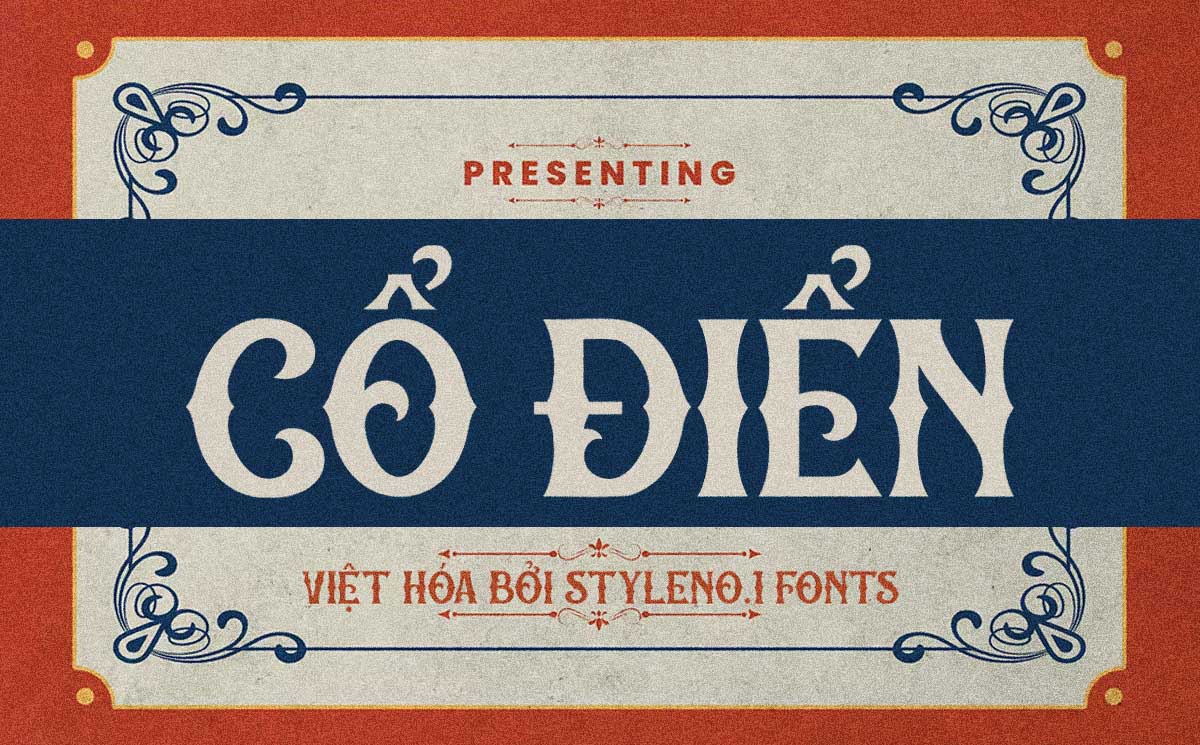
Font chữ phong cách cổ điển, vintage SVN Heimer Việt hóa là một trong những lựa chọn hàng đầu dành cho các nhà thiết kế đang tìm kiếm sự sang trọng, hoài cổ và độc đáo cho dự án đồ họa của mình. Được chế tác tỉ mỉ với bộ đường nét tinh tế cùng khả năng hiển thị tiếng Việt hoàn hảo, bộ phông chữ này mang đến làn gió mới cho các tác phẩm truyền thông và nhận diện thương hiệu. Đặc biệt, bạn có thể dễ dàng tải về và sở hữu bộ phông chữ miễn phí chất lượng cao này để thỏa sức sáng tạo không giới hạn.
Trong xu hướng thiết kế truyền thông hiện đại, phong cách vintage và cổ điển (retro) chưa bao giờ mất đi vị thế vốn có của mình. Việc kết hợp giữa hơi thở hoài cổ của những thập niên trước với ngôn ngữ thiết kế đương đại luôn tạo ra sức hút thị giác đặc biệt đối với người xem. Font chữ phong cách cổ điển, vintage SVN Heimer Việt hóa chính là một tác phẩm typography tuyệt vời đáp ứng trọn vẹn yêu cầu khắt khe đó. Với các đường nét serif sắc sảo, tỉ lệ chữ được tính toán kỹ lưỡng cùng cảm giác ấm áp, phong nhã, SVN Heimer giúp nâng tầm giá trị cho mọi tác phẩm đồ họa. Bộ phông chữ miễn phí này không chỉ đơn thuần là công cụ thể hiện văn bản, mà còn là linh hồn giúp truyền tải câu chuyện thương hiệu một cách giàu cảm xúc nhất.
1. Đường nét hoài cổ mang đậm dấu ấn nghệ thuật vượt thời gian
SVN Heimer sở hữu phong cách thiết kế mang đậm tính lịch sử, gợi nhớ đến các ấn phẩm in ấn cao cấp của thế kỷ 20. Cấu trúc chữ được xây dựng dựa trên sự cân bằng hoàn hảo giữa các nét thanh và nét đậm, tạo nên độ tương phản vừa phải, giúp văn bản vừa dễ đọc vừa giữ được nét quyến rũ riêng biệt. Những chi tiết bo tròn nhẹ nhàng ở chân chữ (serif) kết hợp với các đường cong uốn lượn tinh tế tạo nên vẻ đẹp sang trọng và đẳng cấp. Khi áp dụng vào các tiêu đề lớn, banner quảng cáo hay thiết kế logo, SVN Heimer ngay lập tức thu hút ánh nhìn của thị giác và truyền tải thông điệp về sự uy tín, tinh tế cùng bề dày lịch sử. Đây chính là yếu tố then chốt khiến các nhà thiết kế yêu thích phong cách cổ điển luôn lựa chọn SVN Heimer làm điểm nhấn trong sản phẩm của mình.
2. Bộ ký tự Việt hóa hoàn chỉnh và tối ưu hóa typography
Một trong những rào cản lớn nhất mà các designer tại Việt Nam thường gặp phải khi sử dụng font chữ nước ngoài là lỗi font, thiếu dấu hoặc dấu tiếng Việt bị lệch chuẩn làm mất đi giá trị thẩm mỹ. SVN Heimer Việt hóa đã giải quyết hoàn toàn nhược điểm này khi bộ dấu tiếng Việt được trau chuốt cực kỳ tỉ mỉ và chỉn chu. Các dấu thanh (sắc, huyền, hỏi, ngã, nặng) cũng như các dấu mũ (â, ê, ô, ơ, ư) được thiết kế đồng bộ với nét chữ gốc, đảm bảo khoảng cách giữa các chữ cái (kerning) và độ cao dòng (x-height) luôn hài hòa. Nhờ đó, bất kể bạn soạn thảo đoạn văn ngắn hay tiêu đề dài, phông chữ vẫn giữ được tính chuẩn xác, nét thẩm mỹ tuyệt đối và không bao giờ xảy ra hiện tượng vỡ nét hay sai định dạng.
4. Ứng dụng đa dạng trong nhiều loại hình sản phẩm đồ họa
Với bản chất linh hoạt và thẩm mỹ hoài cổ vượt trội, SVN Heimer Việt hóa không bị giới hạn trong một khuôn mẫu nhất định mà có thể biến hóa đa dạng trên nhiều chất liệu thiết kế khác nhau. Bộ phông chữ này cực kỳ phù hợp cho các dự án nhận diện thương hiệu (branding), thiết kế bao bì sản phẩm thủ công, nhãn mác chai rượu, quán cà phê, nhà hàng mang phong cách retro hay classic. Ngoài ra, SVN Heimer cũng là lựa chọn lý tưởng cho việc thiết kế bìa sách, poster phim, thiệp mời sự kiện, thiệp cưới sang trọng hay các bài đăng truyền thông thu hút trên mạng xã hội như Facebook, Instagram và Pinterest. Dù xuất hiện ở bất kỳ vị trí nào, font chữ cũng tôn lên vẻ đẹp thanh lịch và cuốn hút cho tổng thể tác phẩm.
Gợi ý cách kết hợp font chữ SVN Heimer Việt hóa hiệu quả nhất
Để phát huy tối đa sức mạnh thị giác của phông chữ phong cách cổ điển SVN Heimer Việt hóa, việc phối hợp font chữ (font pairing) đóng vai trò vô cùng quan trọng. Dưới đây là một số nguyên tắc kết hợp giúp sản phẩm đồ họa của bạn trở nên hài hòa và ấn tượng hơn:
• Kết hợp với Font Sans-serif hiện đại: Sử dụng SVN Heimer cho phần tiêu đề chính (Headline) để tạo điểm nhấn cổ điển sâu lắng, sau đó kết hợp cùng một font Sans-serif không chân tối giản như Montserrat, Roboto hoặc Helvetica cho phần nội dung chi tiết (Body text). Sự tương phản giữa nét hoài cổ và nét hiện đại sẽ làm cho ấn phẩm trông rất thời thượng và dễ đọc.
• Phối hợp cùng Font Script (Chữ viết tay): Đối với các thiết kế thiệp cưới, bao bì mỹ phẩm, menu nhà hàng hay thương hiệu thời trang cao cấp, bạn có thể phối SVN Heimer cùng một font chữ viết tay mền mại. Sự kết hợp này mang lại cảm giác nghệ thuật, tinh tế và vô cùng cá tính.